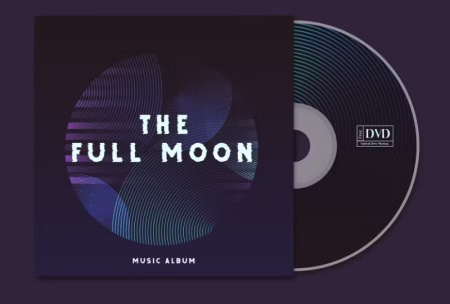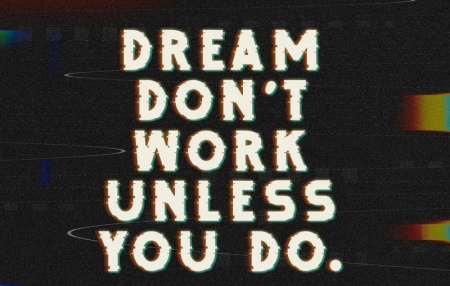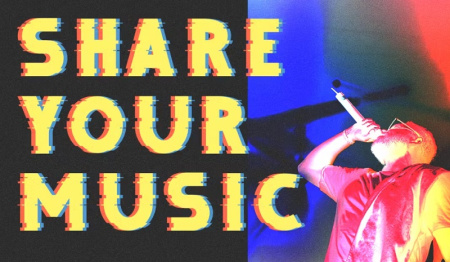
دانلود رایگان فونت انگلیسی گلیچ که به صورت کاملا رایگان در سایت gfx برای دانلود قرار گرفته شده است. شامل حروف های عجیب و غریب که برای نشان دادن جلوه‌ای هنری و مدرن دیجیتال طراحی شده است. این فونت انگلیسی رایگان گلیچ برای نشان دادن ایرادات یا خطاها در هر تصویر دیجیتالی مورد استفاده است. یک فونت زیبا برای آثار هنری یا وب سایت تا فضا و سبکی معاصر به آن ببخشد. این فونت برای برندسازی ، طراحی عنوان بازی یا هر چیزی که فکرش را بکنید عالی است!
✅ نام فونت انگلیسی: Debug
✅ نمادها و علائم نقطه گذاری
✅ اعداد
✅ پشتیبانی چند زبانه